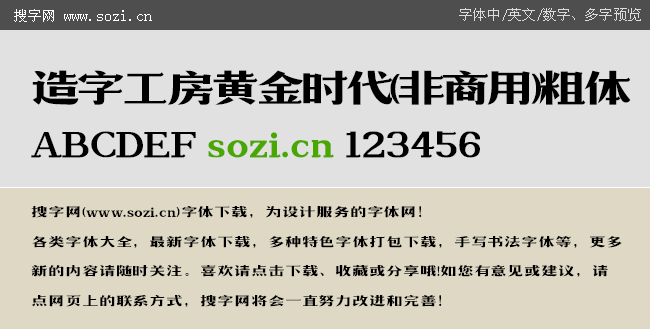
造字工房黃金時(shí)代(非商用)粗體
搜字網(wǎng)提供一款造字工房黃金時(shí)代(非商用)粗體中文字體下載,造字工房黃金時(shí)代體,由造字工房為《黃金時(shí)代》電影定制字體,結(jié)合影片時(shí)代特征,以及主人公蕭紅所處的年代環(huán)境而設(shè)計(jì)。其結(jié)構(gòu)嚴(yán)謹(jǐn),整體風(fēng)格厚重典雅,筆畫飽滿舒展,耐人回味。適用于電影字幕、文字標(biāo)題、廣告設(shè)計(jì)等視覺(jué)環(huán)境,有著極強(qiáng)的應(yīng)用空間。